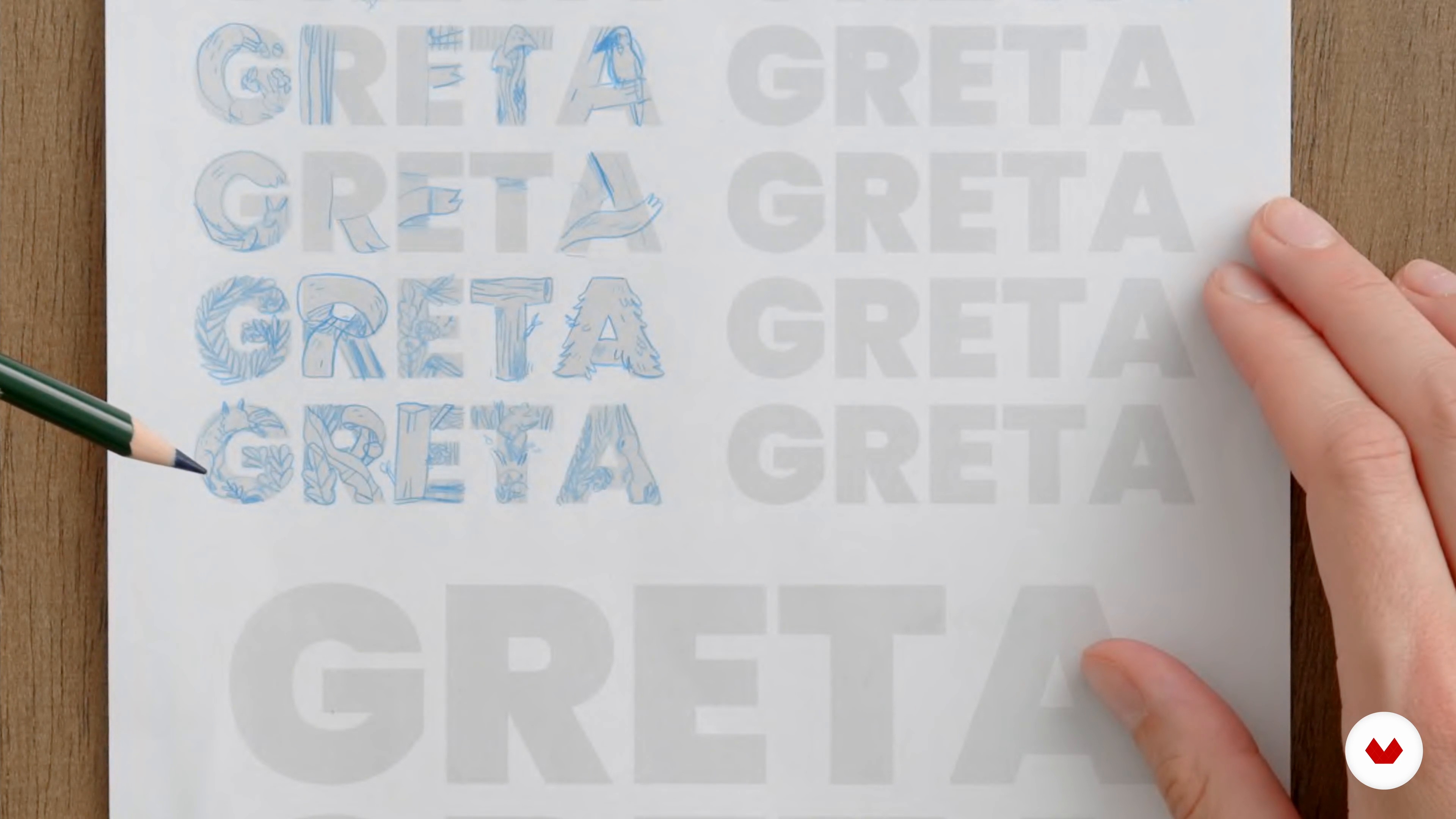
Illustrationen für Kinder: Gestalte eine dekorative Typografie
Kompositionen skizzieren
Ein Kurs von Julia Christians , Illustratorin
Über die Videolektion: Kompositionen skizzieren
“Da wir nun einen (oder mehrere) Buchstaben und ein visuelles Verständnis für unser Thema haben, werden wir die beiden Dinge zusammenführen, indem wir verschiedene Kompositionen erstellen.”
In dieser Videolektion behandelt Julia Christians das Thema: Kompositionen skizzieren, das Teil dieses Domestika-Onlinekurses ist: Illustrationen für Kinder: Gestalte eine dekorative Typografie. Lerne, wie du Typografie und Illustration kombinierst, um mithilfe von analogen und digitalen Techniken eine verspielte Komposition für Kinder zu gestalten.
Partielle Transkription des Videos
“Kompositionen skizzieren Ich zeichne zunächst Miniskizzen, in denen ich verschiedene Kompositionen und Variationen ausprobiere, bis ich mit denen zufrieden bin. Das hat den Vorteil, dass man in kürzerer Zeit möglichst viele Variationen ausprobieren kann, weil die Erstellung einer kleinen Skizze nicht so lange dauert. Im Kleinformat sieht man außerdem gut, ob die Komposition gut funktioniert. Hier noch ein paar Tipps, bevor wir loslegen. Achte bei deiner Zeichnung darauf, dass der Buchstabe lesbar bleibt. Du brauchst die richtige Balance. Lass Objekte aus dem Buchstaben herausragen, aber nic...”
Zusammenfassung des Kurses: Illustrationen für Kinder: Gestalte eine dekorative Typografie